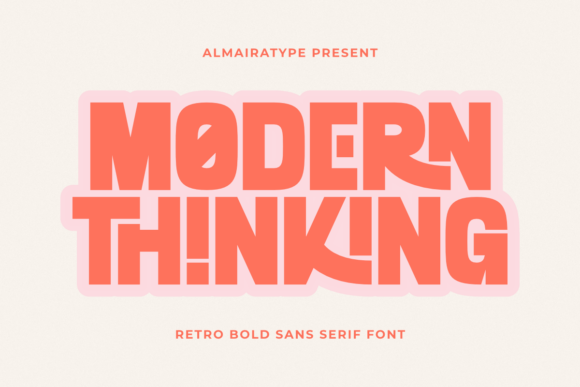
Modern Thinking
Modern Thinking – La police rétro qui dynamise vos projets modernes
Vous cherchez une police qui marie l’énergie du street‑wear contemporain avec la nostalgie chic des années 70 ? Modern Thinking est la réponse. Cette police sans‑serif rétro, audacieuse et ultra‑ludique, a été conçue spécifiquement pour les designers qui veulent une typographie à la fois lisible, impactante et riche d’une personnalité vintage unique.
Pourquoi Modern Thinking séduit les créateurs ?
- Poids massif et structure géométrique – chaque glyphe possède une épaisseur généreuse qui garantit une visibilité maximale, même à petite taille.
- Caractères alternatifs exclusifs – des variantes stylisées qui ajoutent une touche d’originalité à chaque composition.
- Compatibilité totale avec les outils de découpe – les contours nets fonctionnent parfaitement avec Cricut, Silhouette et autres découpeurs vinyle, simplifiant le weeding pour stickers, mugs et projets DIY.
- Polyvalence commerciale – idéale pour les identités de marque, les collections de t‑shirts, les packagings, les affiches réseaux sociaux et le Print‑on‑Demand.
- Lisibilité exceptionnelle – même en impression petite ou sur écran, les lettres restent claires et nettes.
Pour qui est faite Modern Thinking ?
- Graphistes professionnels à la recherche d’une typographie qui sort du lot.
- Marques de vêtements indépendantes désireuses d’allier rétro et modernité.
- Passionnés de DIY et créateurs de stickers, mugs, et articles découpés.
- Entrepreneurs POD qui veulent des designs à haut taux de conversion.
Comment exploiter Modern Thinking dans vos projets
Utilisez‑la pour créer des titres percutants, des logos mémorables ou des slogans qui restent gravés dans l’esprit. Son style rétro‑futuriste fonctionne à merveille sur les:
- Affiches publicitaires et bannières de réseaux sociaux.
- Étiquettes de produits et packaging premium.
- Collections de t‑shirts et sweats à la mode street‑wear.
- Designs de stickers et d’articles personnalisés pour le marché du DIY.
Conclusion – Un atout incontournable pour votre boîte à outils créative
Modern Thinking ne se contente pas d’ajouter une touche vintage ; elle réinvente le look rétro avec une modernité qui séduit les audiences d’aujourd’hui. Que vous soyez un designer chevronné ou un entrepreneur POD, cette police vous offre la puissance visuelle et la flexibilité technique nécessaires pour transformer chaque projet en un succès commercial.